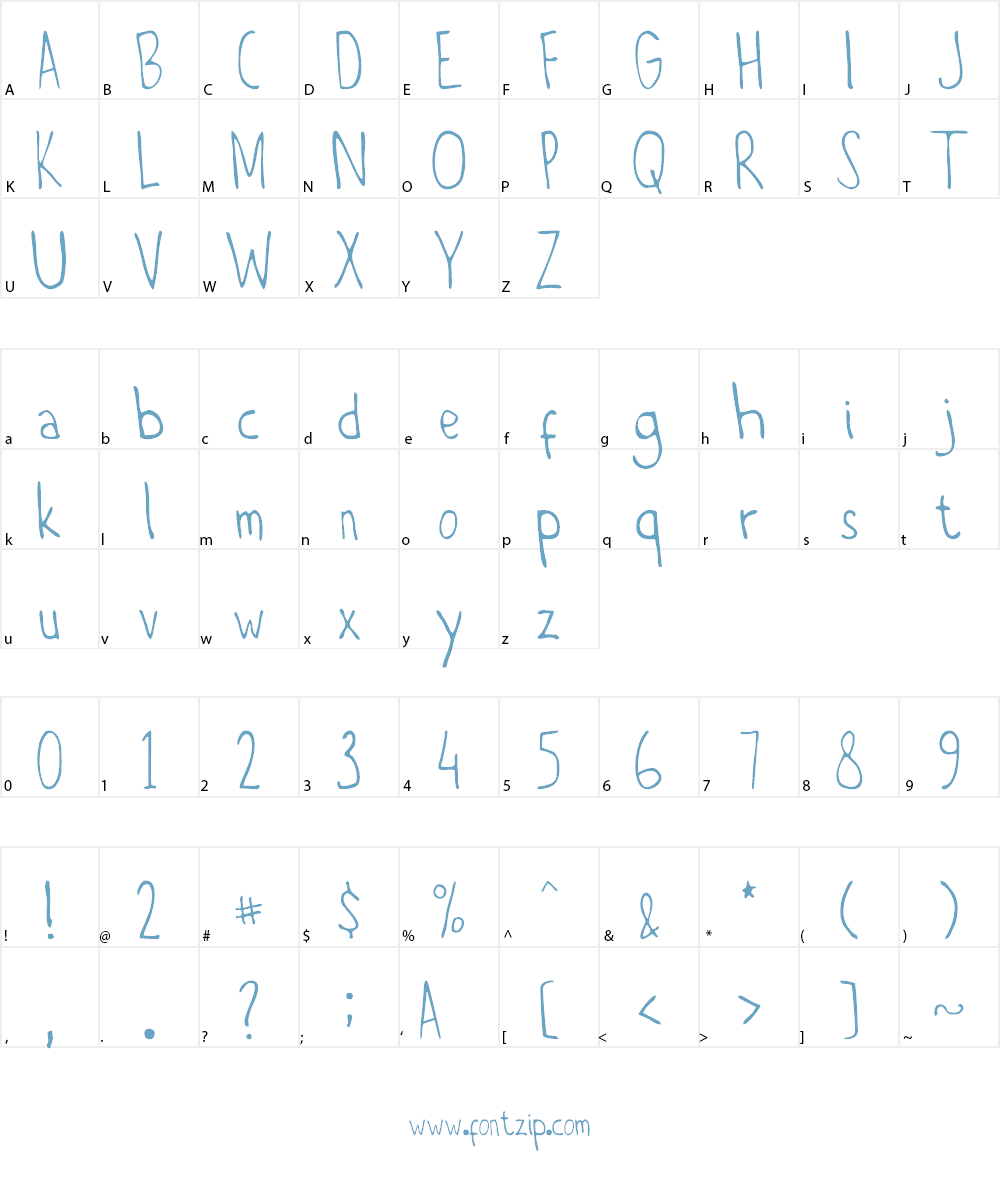
Font untuk menciptakan kesenagan pada lembar kerja anda, untuk para kreatif yang menyukai gaya bebas.
This font for happiness theme for your workspace, for creative people who's interesting about free style.